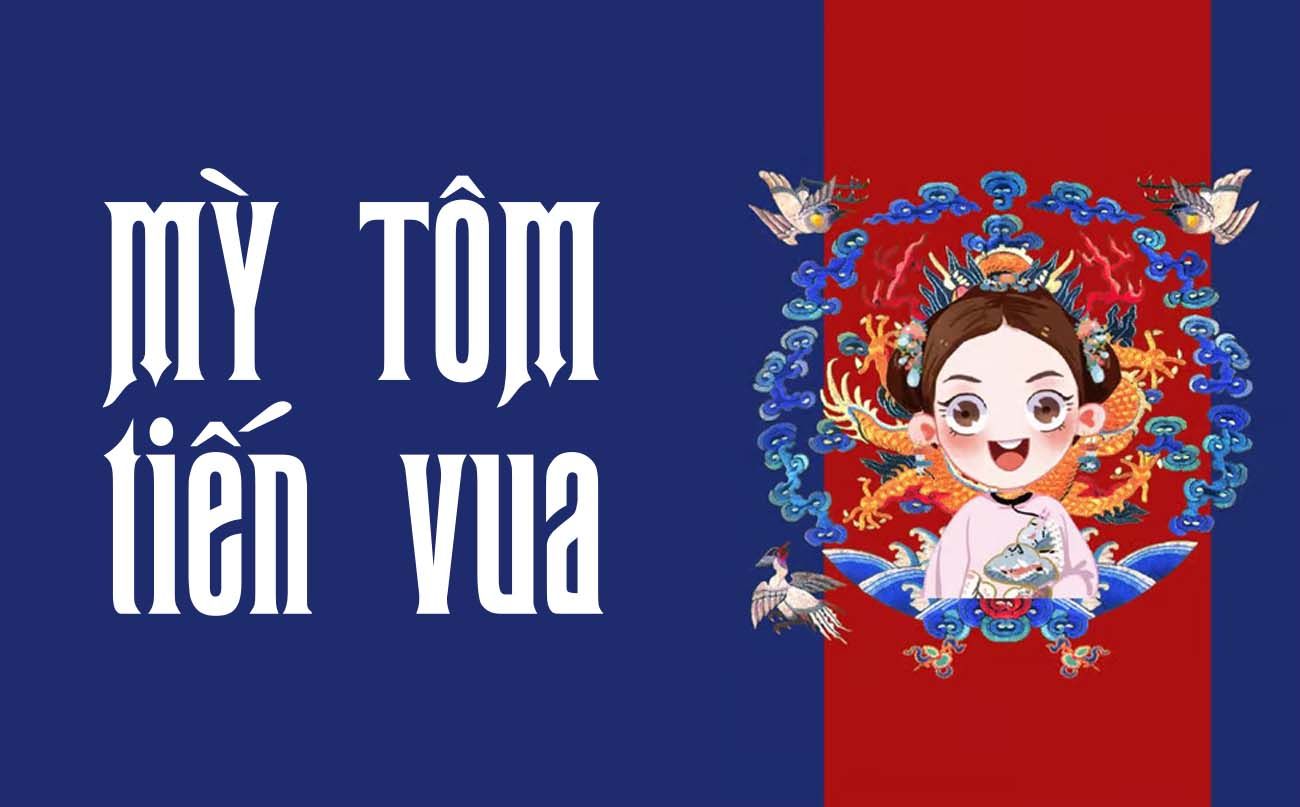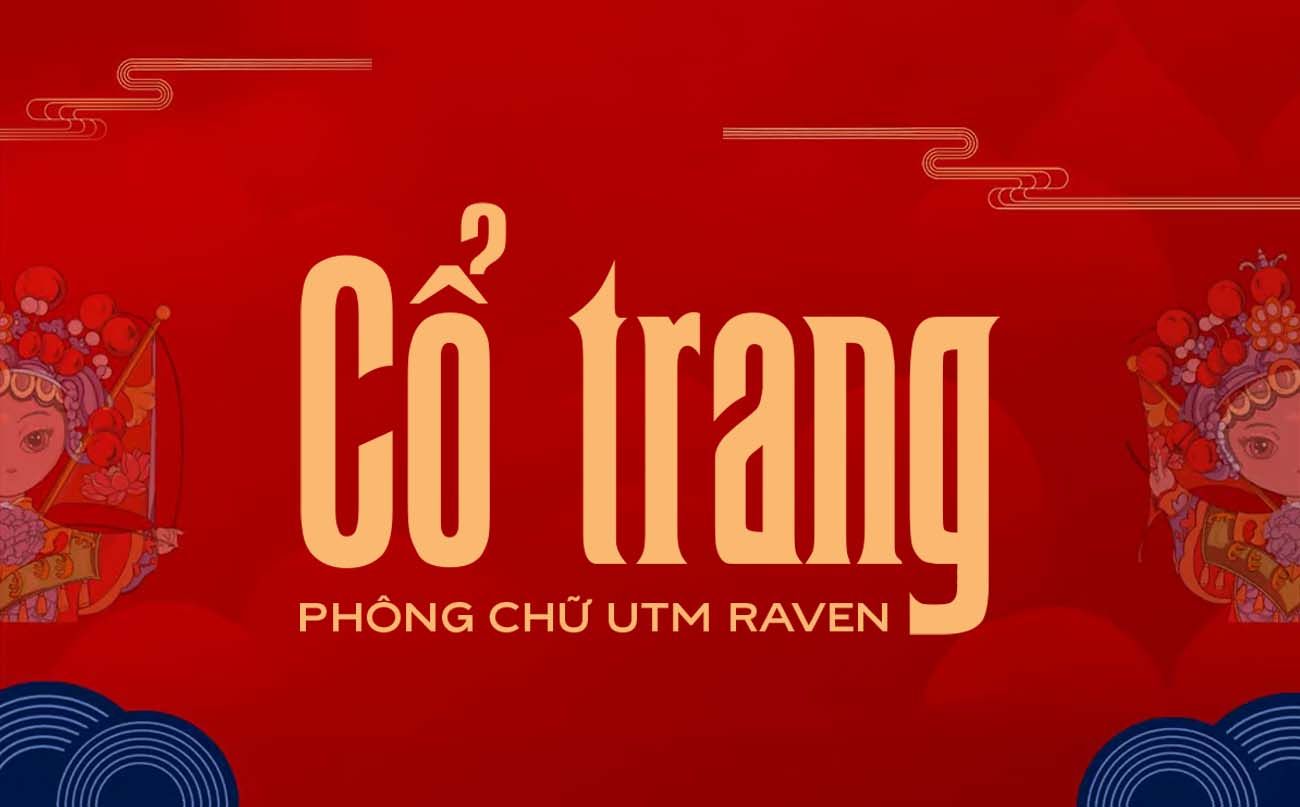
[Tải Về] Font UTM Raven – Font Việt Hóa Cổ Trang Cứng Cáp Mang Dáng Dấp Cung Đình Xưa
Nếu bạn đang tìm kiếm một font Việt hóa mang khí chất cung đình cổ xưa, vừa uy nghiêm, cứng cáp, lại có nét thư pháp phương Tây xen lẫn hơi thở Á Đông, thì UTM Raven là lựa chọn đầy sức nặng. Với kiểu chữ mang đậm phong cách serif hoàng gia cổ, UTM Raven rất phù hợp cho các thiết kế gắn liền với văn hóa cung đình, tranh cổ phong, hoặc giao diện game cổ trang.
UTM Raven – Chất liệu chữ của triều đình và di sản
UTM Raven không phải là một font hiện đại kiểu tối giản. Trái lại, nó sở hữu nét serif sắc cạnh, đầu móc – chân kéo, mang lại cảm giác như đang đọc sắc phong, chiếu chỉ hay văn bản triều đình xưa.
Được Việt hóa hoàn chỉnh bởi nhóm Urban Type Management (UTM), bộ font này hỗ trợ đầy đủ tiếng Việt, giữ nguyên khí chất mạnh mẽ của bản gốc, đồng thời hài hòa với ngôn ngữ Á Đông.
Vì sao UTM Raven phù hợp với thiết kế cung đình & cổ trang?
1. Font serif sắc sảo – nét bút của quyền uy
UTM Raven sử dụng các đường cong cứng, nét móc dài và nhọn, tái hiện lại dáng chữ thường thấy trong sắc chỉ, bảng hiệu phủ quan, hay bìa sách chữ Hán xưa. Chữ có trọng tâm, tạo nên cảm giác quyền lực và nghiêm trang.
2. Việt hóa trọn bộ – dùng tốt cho cả Hán Việt và hiện đại
Font hỗ trợ đầy đủ dấu tiếng Việt, hiển thị sắc nét trên mọi nền tảng từ in ấn đến kỹ thuật số. Khi kết hợp với từ Hán Việt hoặc văn bản mô phỏng cổ phong, UTM Raven thể hiện rõ phong cách của một dòng chữ cung đình thời cũ.
3. Dễ kết hợp với đồ họa cổ trang
Dù là poster phim cổ trang, tranh vẽ Hán học, banner hội làng, hay game kiếm hiệp, UTM Raven đều có thể hòa nhập một cách mượt mà, tôn vinh yếu tố văn hóa – truyền thống – nghi lễ.
Kết luận
Dù không mang nét thư pháp uốn lượn, UTM Raven lại truyền tải được cái cốt cách cứng cỏi, trầm mặc và đầy nội lực. Với những ai theo đuổi phong cách thiết kế cổ trang, nghi lễ hoặc hoài cổ cung đình, đây là một bộ font có chiều sâu và giá trị thẩm mỹ cao.